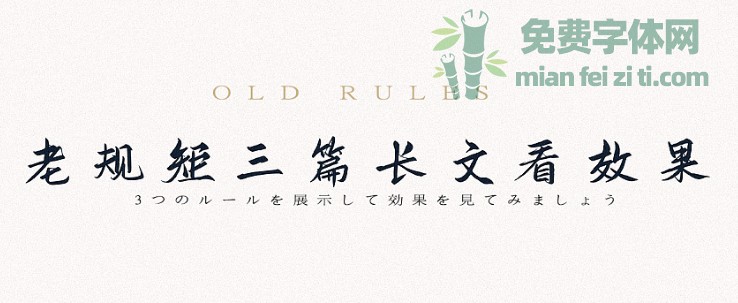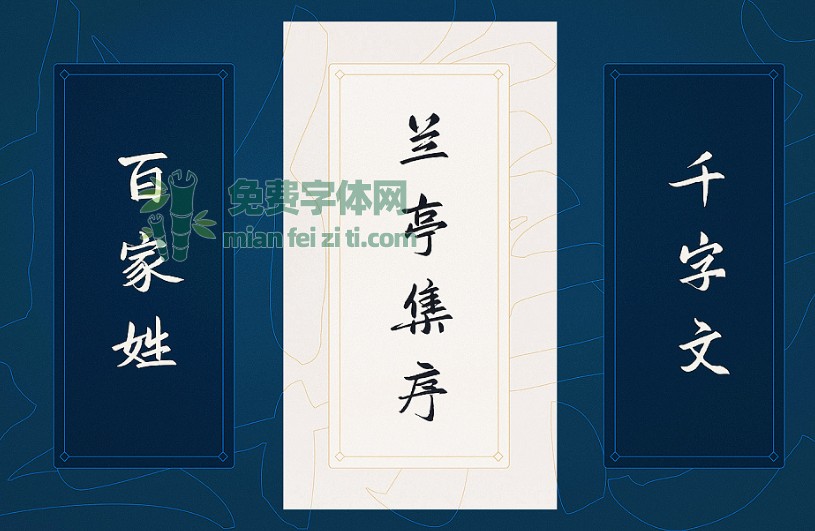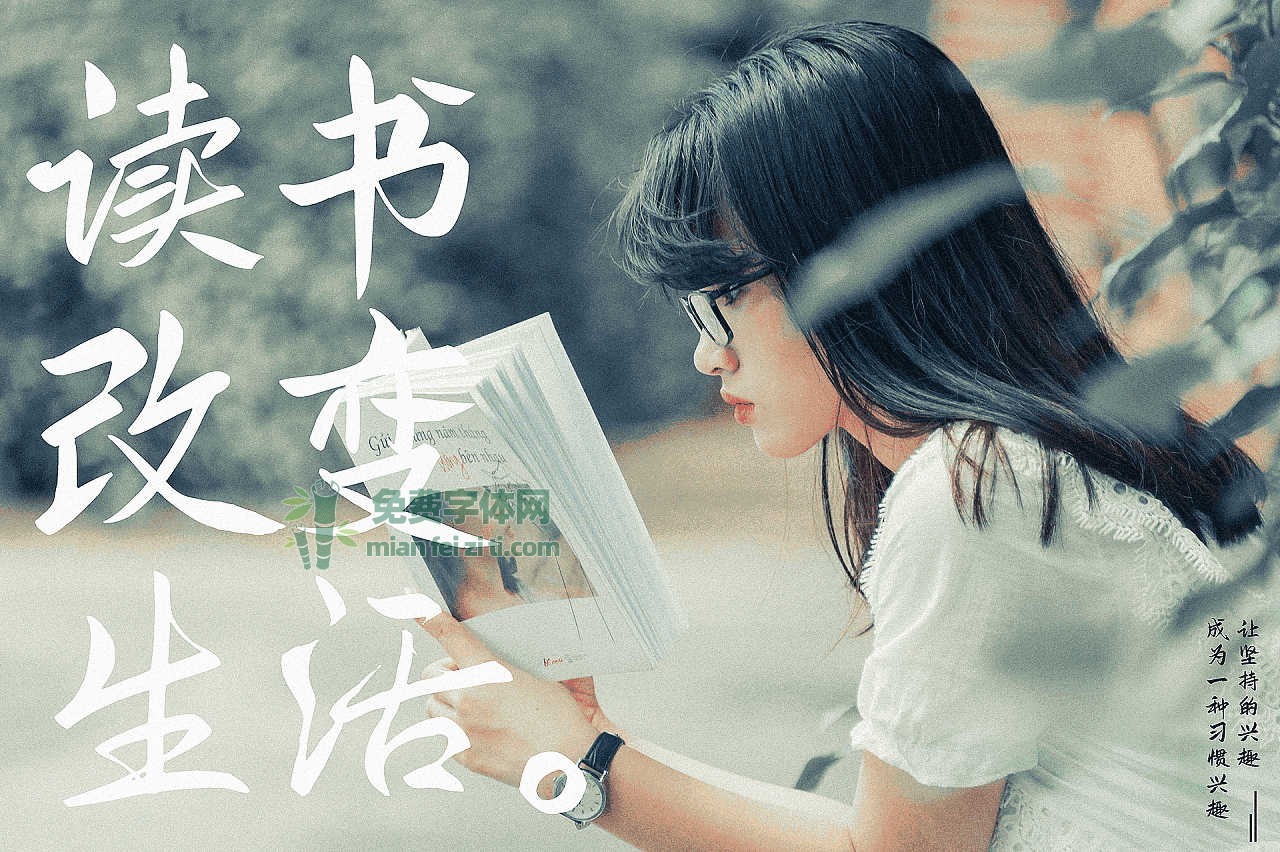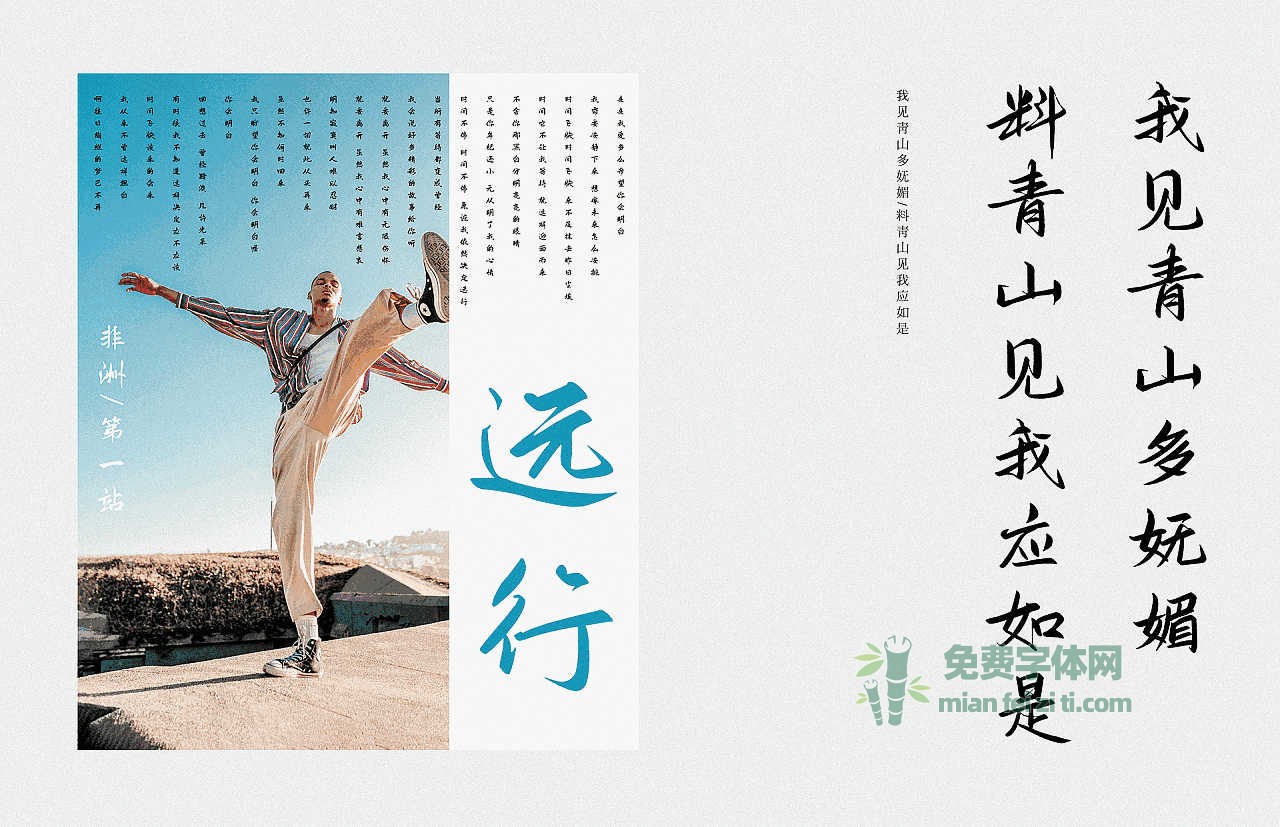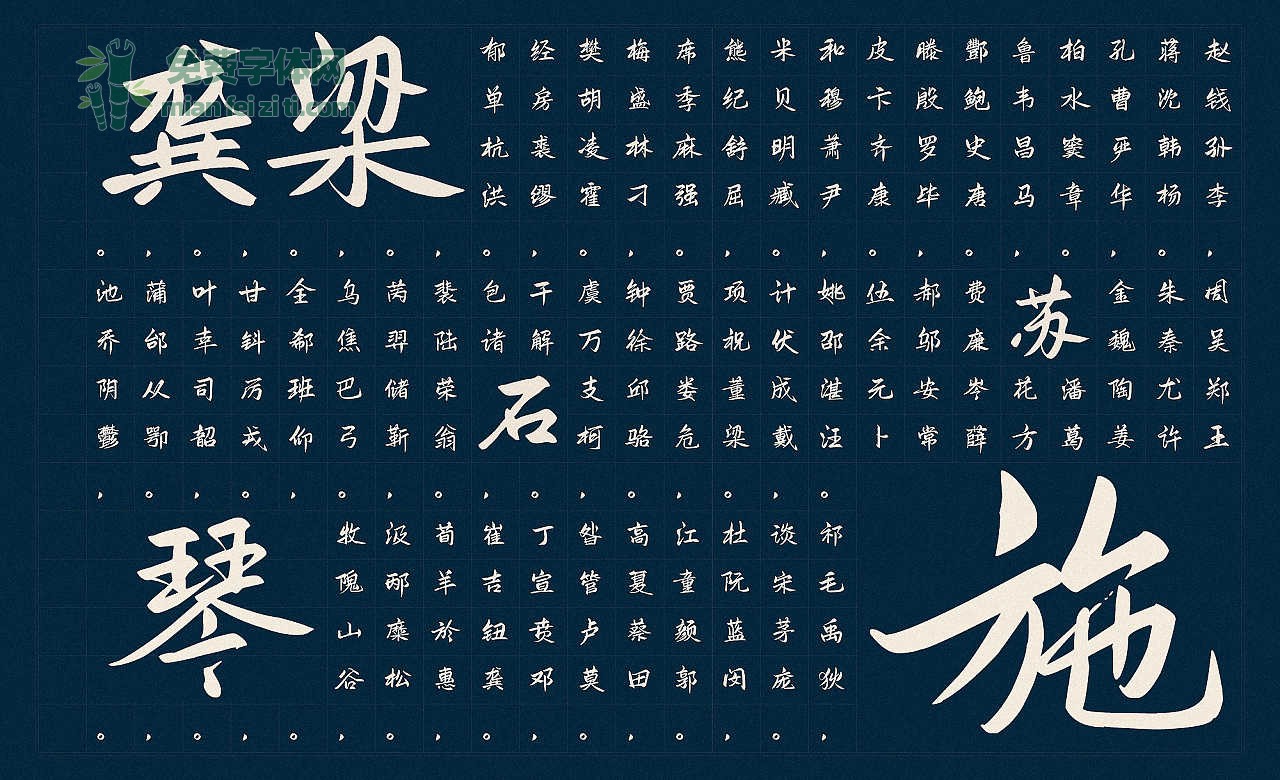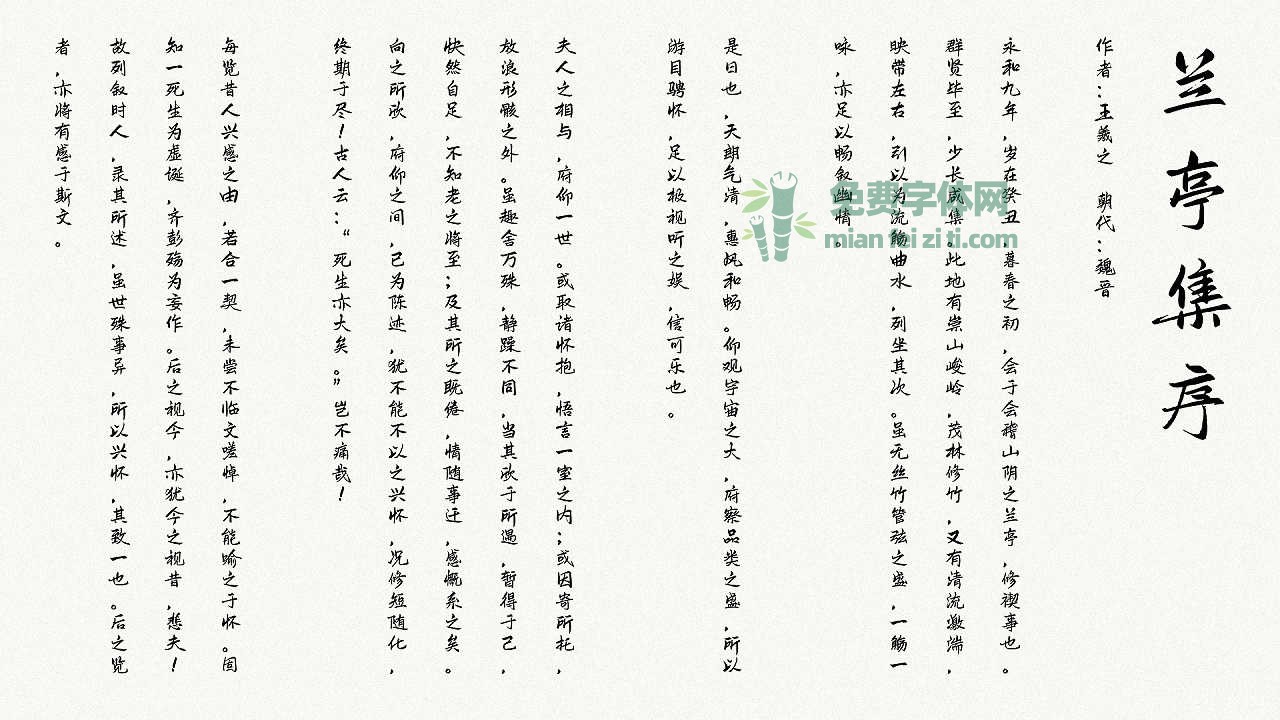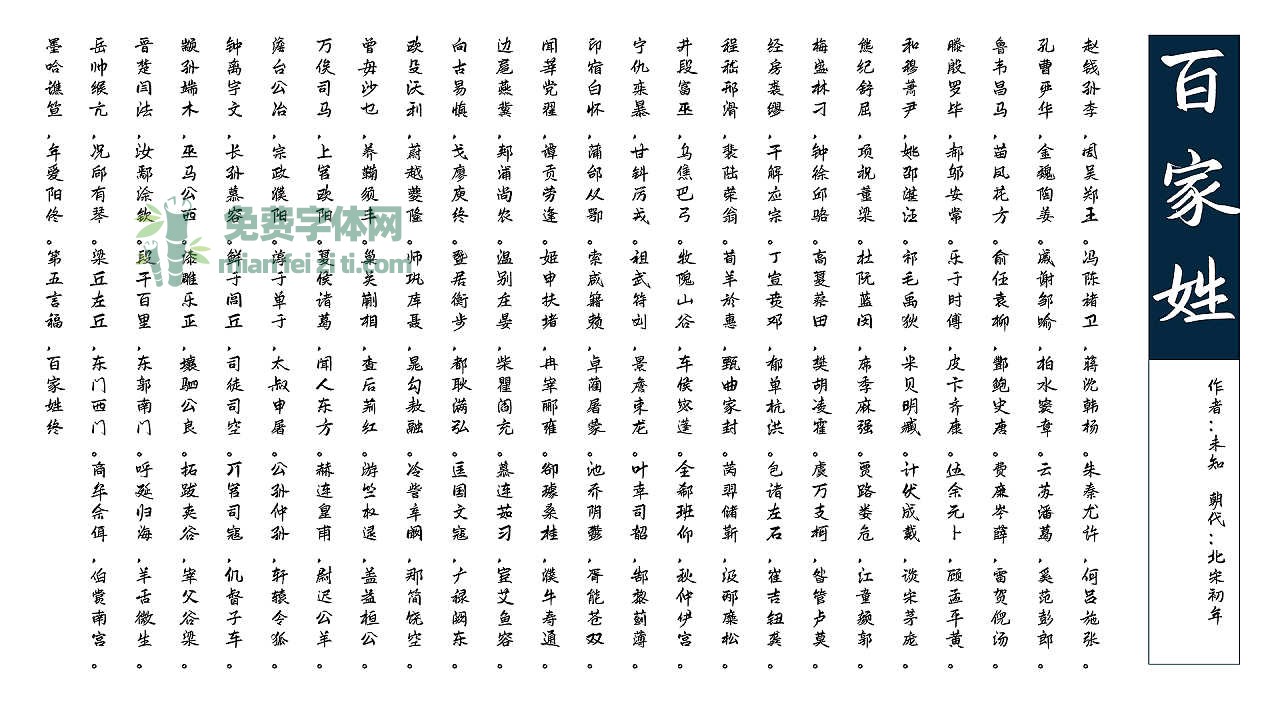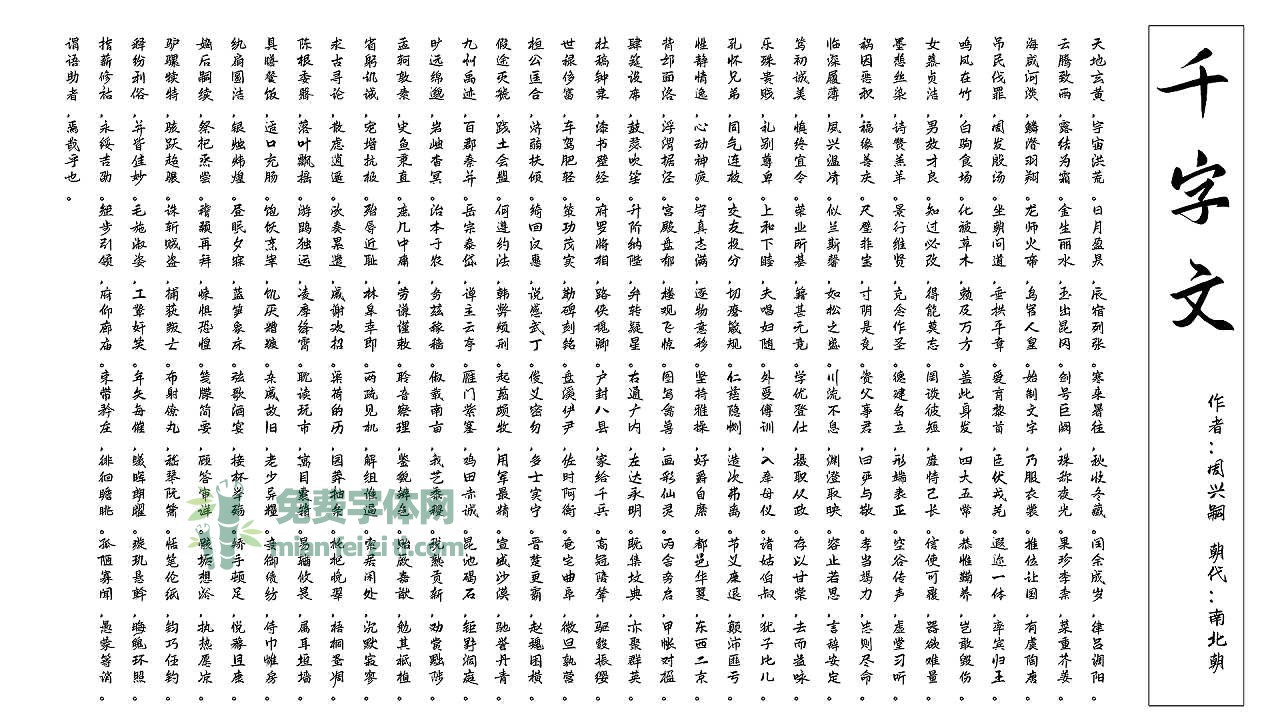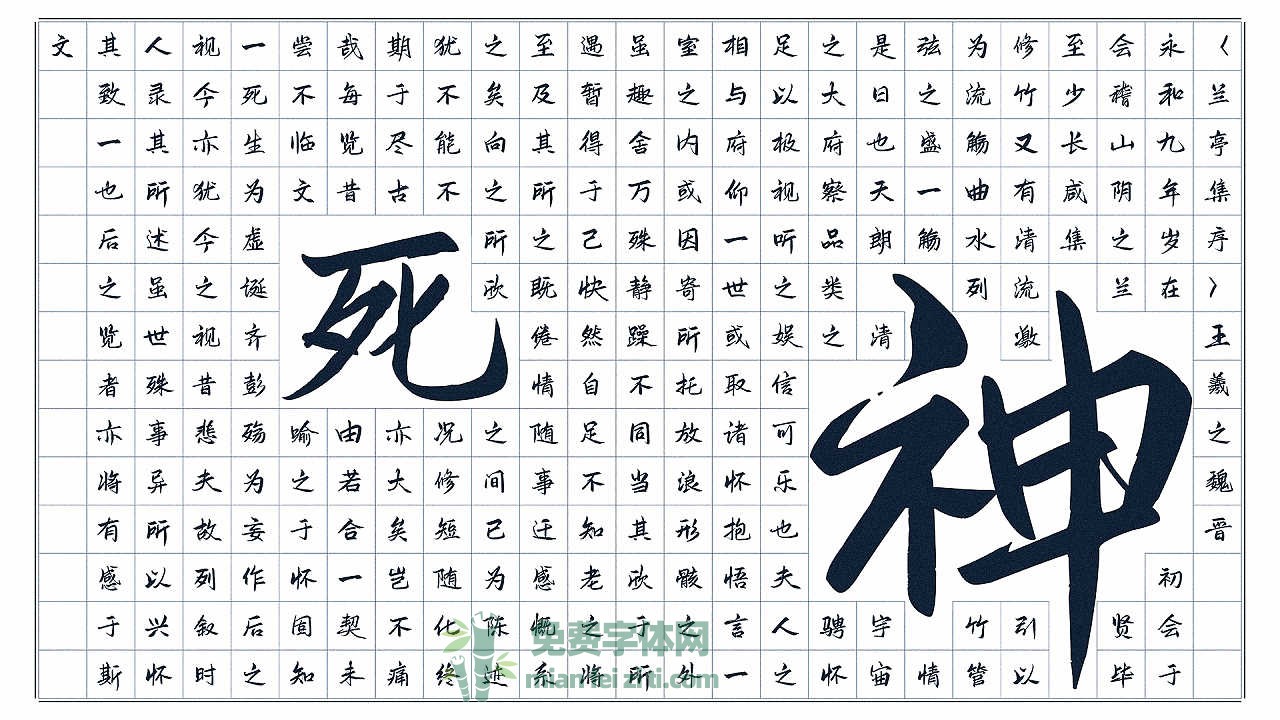
今天给伙伴们分享一个超级漂亮的手写字体《 鸿雷板书简体 》。在一个月之前,鸿雷字迹在站酷上就透露将会发布一款免费商用的手写字体,那时我看到这款字体的真容,心理就超级期待,因为实在是太漂亮了。大家可以移步站酷看下大神发表的《 啄字丨鸿雷板书字体A(简) 》文章。
大神这样说:
关于如何看待这个字体我是这么想的“作为一个手写爱好者,我没有经过传统书法的熏陶与练习,走上了江湖道路,凭借满腔喜爱坚持写下这套字体。或许……这套糟糕的字体会拉低了行业字库的水准,但不管好坏也算是圆了我的字库梦想。”
1、如果要问起为什么要写这个套字体?
最初源于练字……当时没有什么可以写的内容,于是想到了抄写千字文。再后来,嗯,都写了1000字了,也不差剩下的五六千字了。于是就有了《鸿雷板书简体》。
2、为什么叫板书简体呢?
因为他是用手绘板写的简体部分
3、如果问到我将如何看待或者如何处置这个《鸿雷板书简体》?